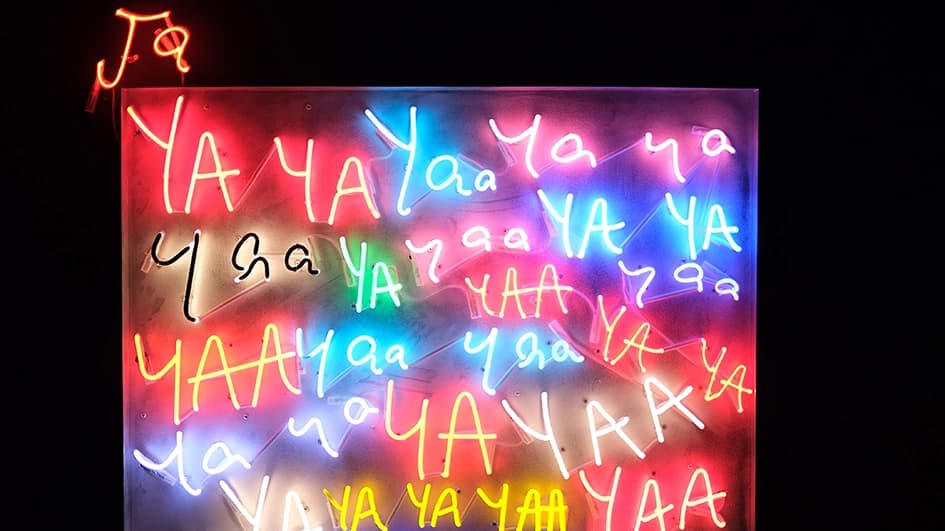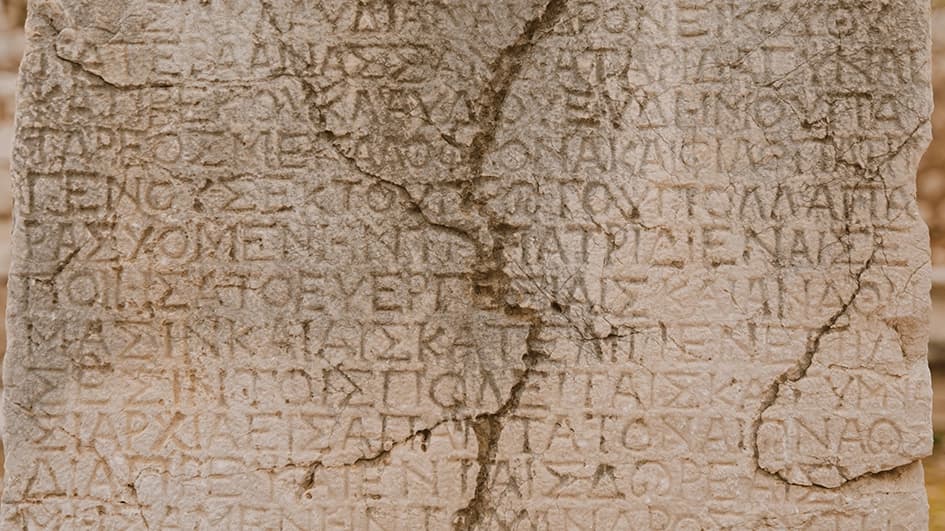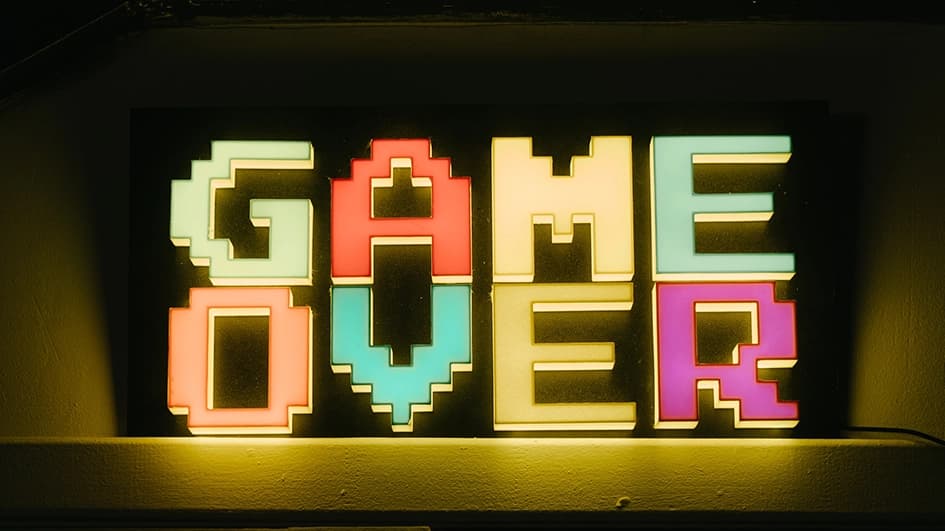
5 astuces de graphiste pour choisir les typographies de votre entreprise
Les 5 astuces qui vous manquaient pour avoir une image professionnelle grâce au choix des typographies de votre entreprise.
En bref : pour choisir les typographies de votre entreprise, privilégiez des polices lisibles, libres de droits, professionnelles, alignées avec vos valeurs et intemporelles. Limitez-vous à trois typographies complémentaires : une pour les titres, une pour le texte courant et une plus originale pour apporter des touches de dynamisme.
Le choix des typographies d’une identité visuelle est crucial pour permettre à votre entreprise de se développer comme vous le désirez et atteindre son coeur de cible.
En plus des typographies utilisées dans votre logo, vous devez déterminer dès la création de votre marque, quelles seront les typographies que vous utiliserez quotidiennement sur vos documents officiels, votre site internet, votre communication print, vos réseaux sociaux, etc.
Il est préférable de faire appel à un graphiste spécialisé mais si vous souhaitez tout de même vous lancer seul dans cette tâche, voici 5 astuces qui vous aideront à faire les bons choix !
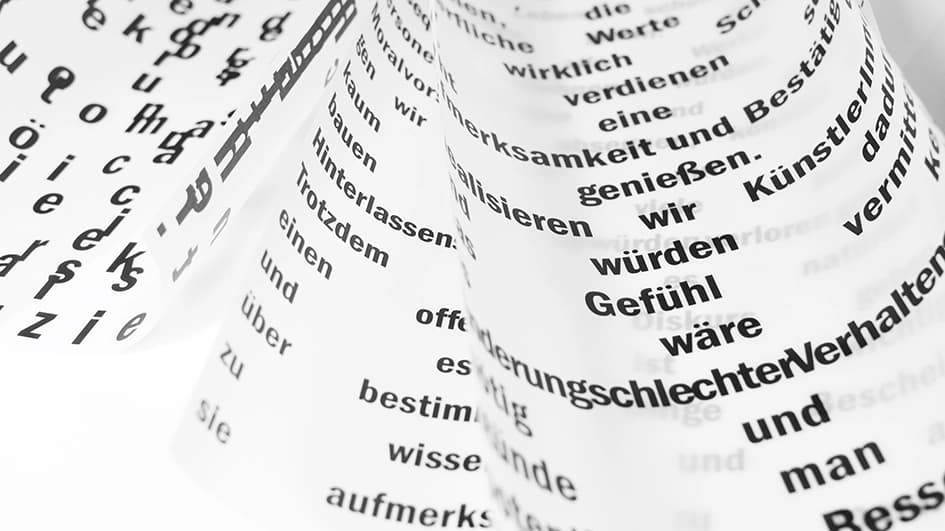
Astuce 1 : Des typographies lisibles
Assurez-vous que le texte soit facile à déchiffrer
Lorsque vous choisissez des typographies pour votre entreprise, la lisibilité doit être votre priorité. Votre message doit être clair et accessible pour tous vos publics, qu’il s’agisse de clients, de partenaires ou de prospects. Les typographies complexes, avec des ornements exagérés ou des lettres mal définies, peuvent rendre la lecture difficile et frustrante. Optez pour des polices épurées et nettes qui garantissent que votre contenu est compréhensible au premier coup d’œil.
N’oubliez pas les accents et caractères spéciaux !
Si votre entreprise cible un public français ou international et utilise des langues autres que l’anglais, n’oubliez pas de vérifier que les typographies que vous utilisez prennent en charge les accents et les caractères spéciaux nécessaires. Il est essentiel que votre contenu soit correctement représenté dans toutes les langues cibles pour éviter toute confusion ou malentendu.
Astuce 2 : Des typographies libres de droits
Lorsque vous choisissez des typographies pour votre entreprise, assurez-vous qu’elles sont libres de droits ou que vous avez les licences appropriées pour les utiliser. L’utilisation de typographies sous licence sans autorisation peut entraîner des litiges juridiques coûteux. Optez pour des polices open source ou achetez des licences pour éviter tout problème juridique potentiel.
Astuce 3 : Des typographies professionnelles
Vous n’êtes pas sur le Skyblog que vous aviez à 15 ans
Évitez les typographies exagérées, enfantines ou peu professionnelles qui pourraient nuire à la crédibilité de votre entreprise. Les typographies trop fantaisistes peuvent donner l’impression que votre entreprise manque de sérieux. Optez pour des polices professionnelles, épurées et élégantes qui renforcent la confiance en votre marque et laissez la Comic Sans MS là où est sa véritable place : dans vos souvenirs.
Faites de la veille concurrentielle
La veille concurrentielle est une étape cruciale lors du choix de typographies pour votre entreprise. Analysez les typographies utilisées par vos concurrents directs et identifiez celles qui fonctionnent le mieux pour votre secteur. Déterminez type de police vous semble le plus professionnel lors de vos recherches. Cela vous aidera à rester cohérent avec les normes pratiquées dans votre activité tout en vous permettant de vous démarquer.
Astuce 4 : Des typographies qui renvoient les bonnes valeurs
Trouvez votre client idéal
Pour choisir les typographies qui reflètent les bonnes valeurs, commencez par définir votre client idéal. Quel type de public souhaitez-vous attirer ? Quels sont les traits de caractère que vous voulez associer à votre entreprise ? Les typographies peuvent véhiculer des émotions et des valeurs, alors assurez-vous qu’elles correspondent à l’image que vous souhaitez projeter.
Déterminez quel type de typographie correspond à vos valeurs
Si votre entreprise se concentre sur l’écologie, par exemple, optez pour des typographies organiques et durables. Si vous visez un public jeune et moderne, des typographies audacieuses et contemporaines pourraient être plus adaptées. Assurez-vous que vos typographies reflètent les valeurs de votre entreprise de manière authentique. Pour vous aider dans la symbolique des typographies, vous pouvez vous aider de l’article consacré à ce sujet.
Astuce 5 : Des typographies intemporelles
Ne suivez pas les tendances
Les tendances en matière de typographie peuvent changer rapidement, et il est tentant de suivre la dernière mode. Cependant, il est important de garder à l’esprit que les typographies trop à la mode risquent de rapidement paraître démodées. Optez pour des typographies intemporelles qui resteront pertinentes et élégantes au fil des années. Cela vous permettra de conserver une cohérence dans votre communication sur le long terme et d’être reconnaissable pour vos clients. Si vous changez trop souvent de typographies, vous prenez le risque de renvoyer l’image d’une entreprise changeante et non fiable et de perdre vos clients, qui ne comprendront pas ces évolutions incessantes.
Conclusion
En conclusion, le choix des typographies pour votre entreprise est une décision cruciale qui peut influencer l’efficacité de votre communication visuelle. Assurez-vous de privilégier la lisibilité, la légalité, la professionnalisme, l’alignement avec vos valeurs et l’intemporalité. En suivant ces cinq astuces de graphiste, vous serez en mesure de créer une identité visuelle forte et durable pour votre entreprise.